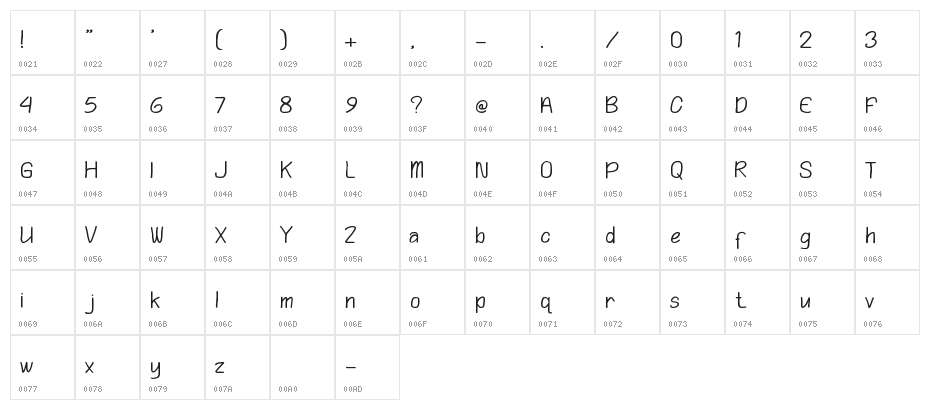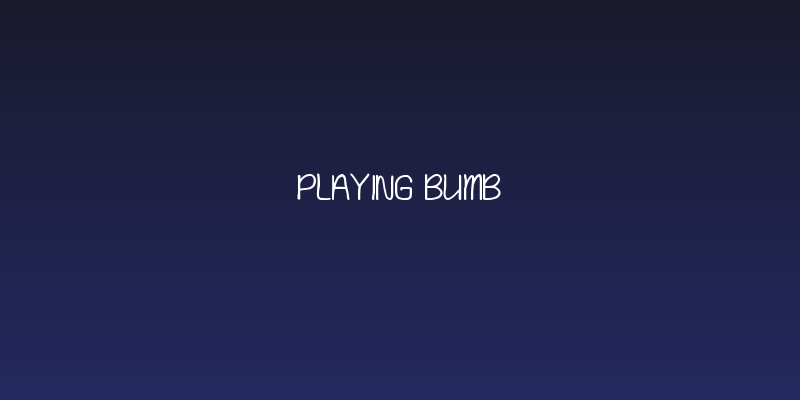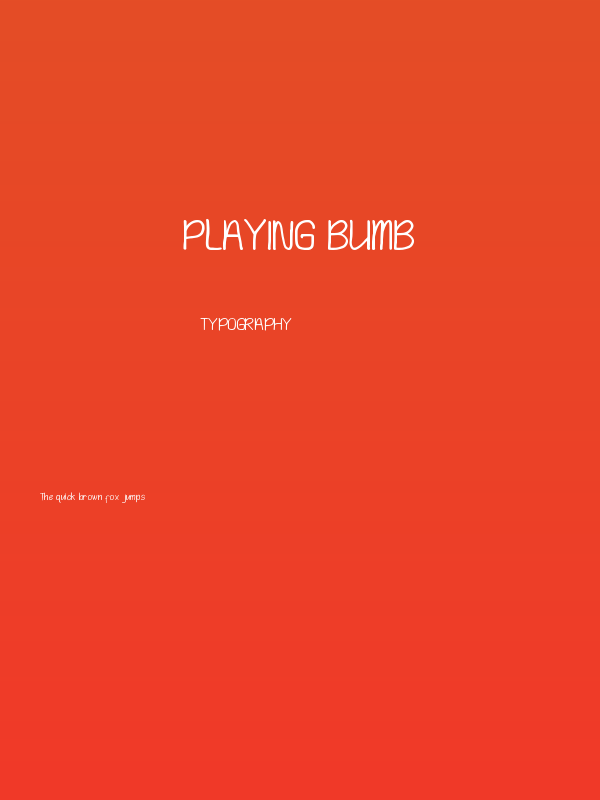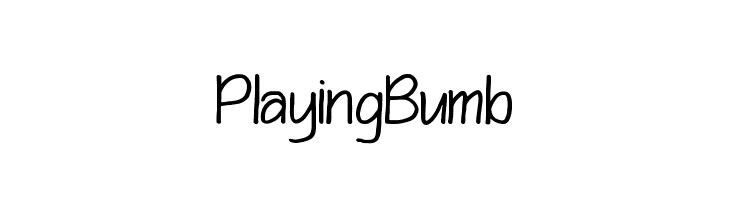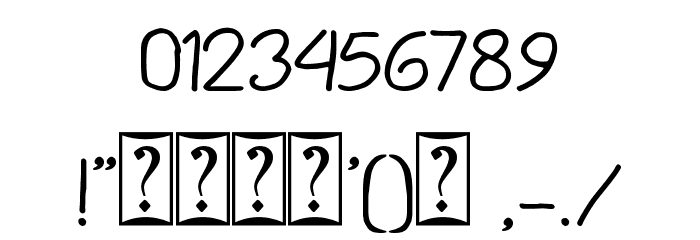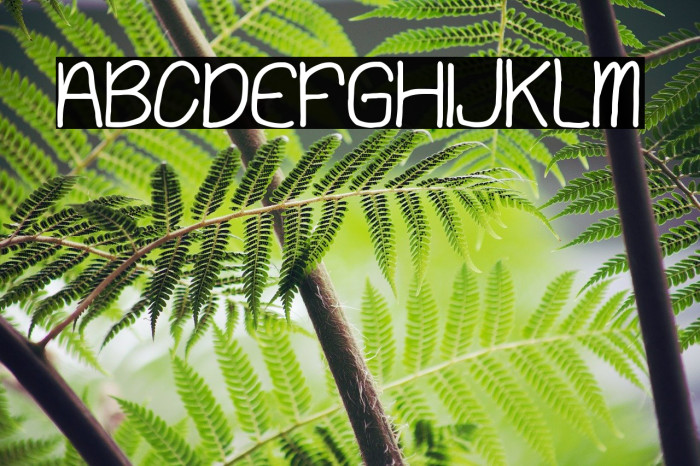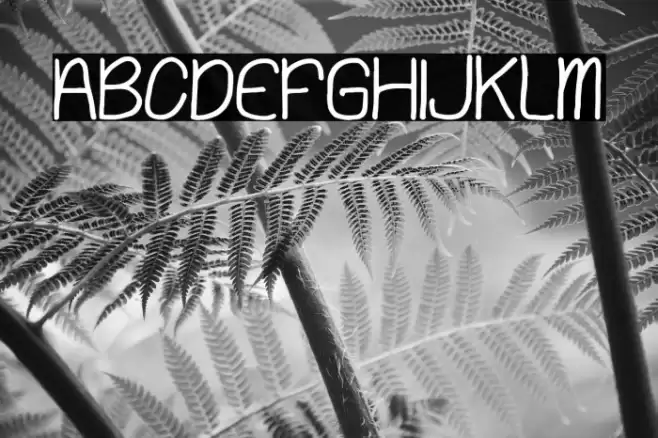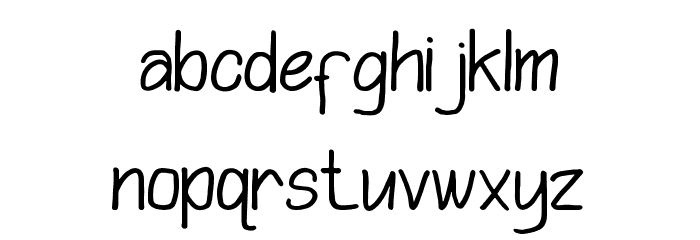
Playing Bumb Font
| Gesamtstil | Casual, Playful |
| Anwendungsfall | Headlines, Informal text, Creative projects |
| Vorgeschlagene Projekte | Great for greeting cards, children's books, playful branding, and casual invitations. |